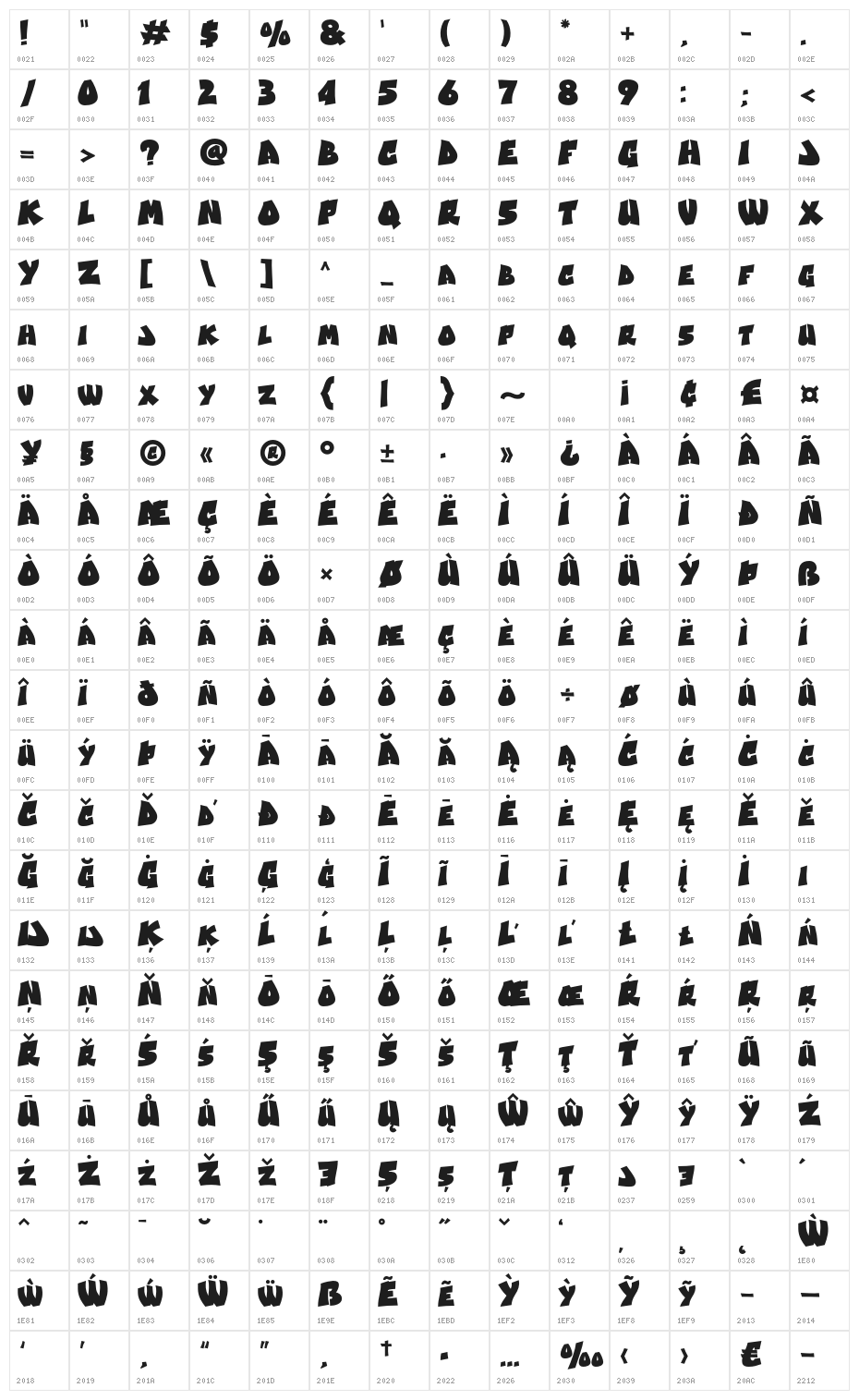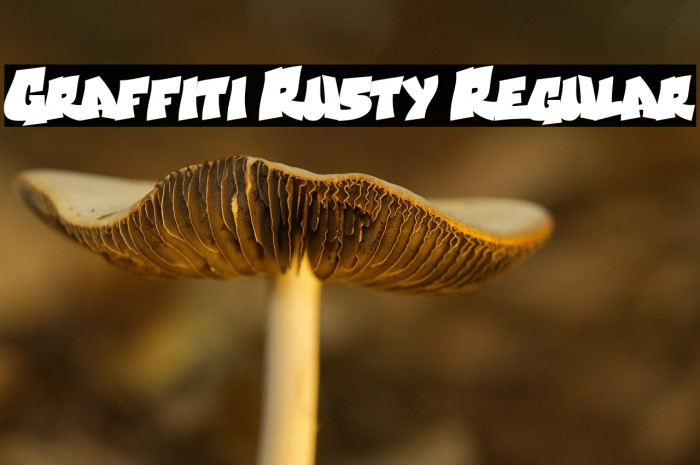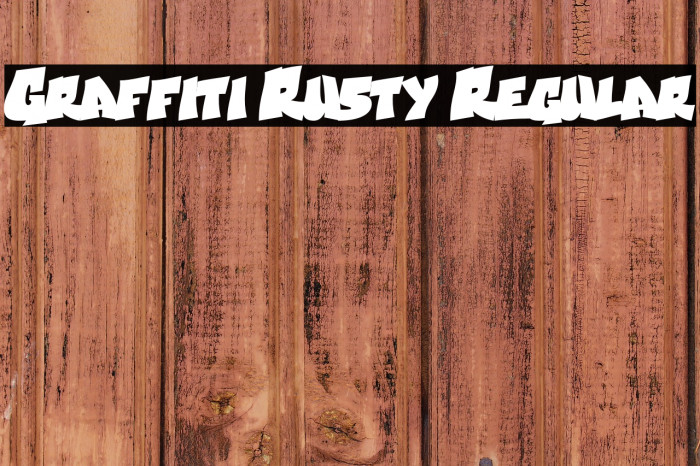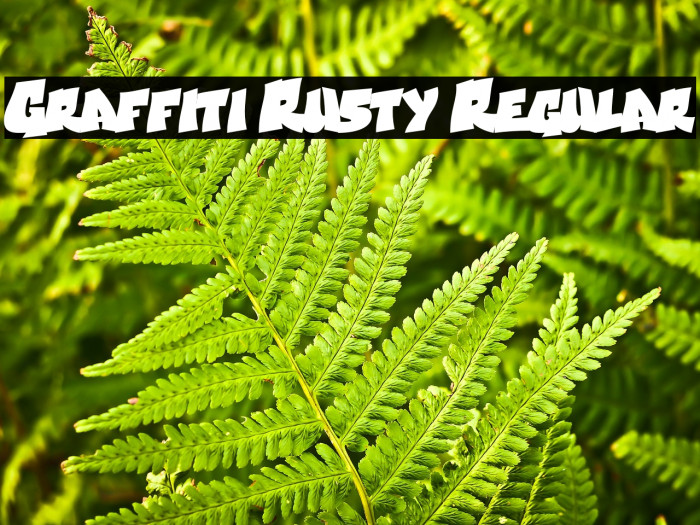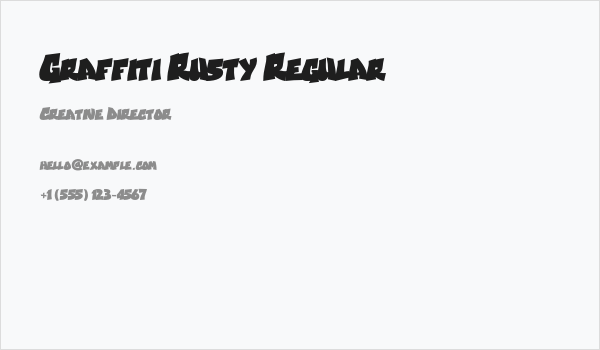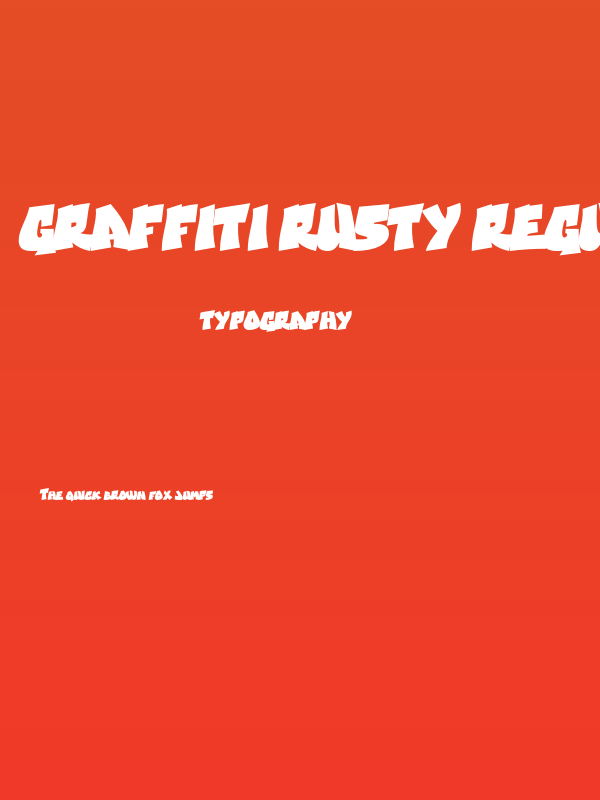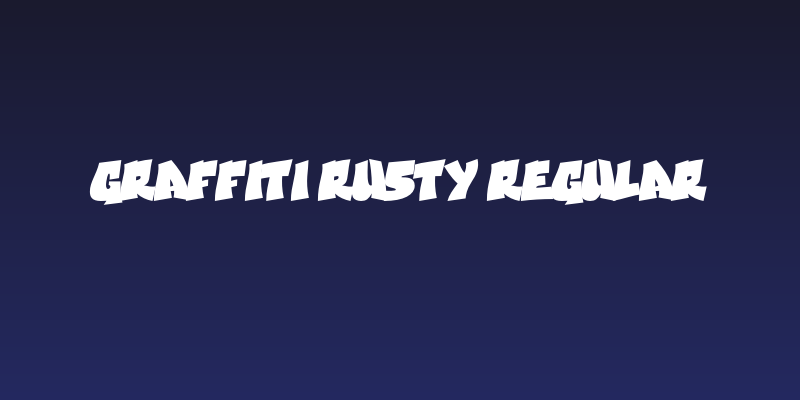
Graffiti Rusty Regular Font
| Categorías | Graffiti |
| Estilo general | Urban, Edgy, Graffiti |
| Proyectos propuestos | Ideal for street art designs, urban-themed posters, music album covers, and edgy branding projects. |